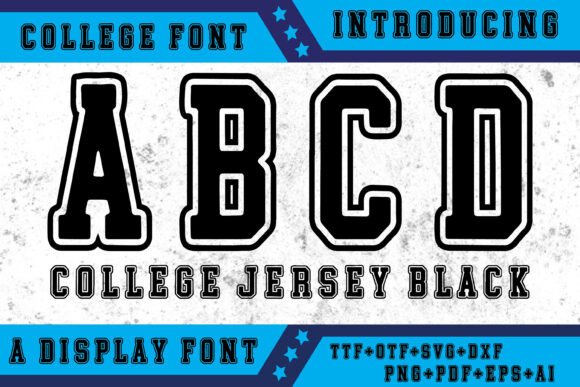
College Jersey Black
College Jersey Black – A Fonte que Transforma Seu Projeto em Vitória
Se você busca energia, tradição e personalidade vibrante para suas criações, a College Jersey Black é a escolha certeira. Essa tipografia, inspirada nos uniformes esportivos e nas artes gráficas de campus, combina contornos fortes e estrutura em bloco para entregar impacto visual imediato.
Ideal para branding, embalagens, logotipos e títulos chamativos, a fonte se destaca em projetos que precisam de voz autoritária sem perder a alegria contagiante. Veja a seguir os principais atributos que fazem da College Jersey Black um must‑have para designers:
- Design arrojado e block‑style: linhas grossas que garantem legibilidade mesmo em tamanhos reduzidos.
- Versatilidade esportiva: perfeita para uniformes, camisas de time, flyers de torneios e pôsteres de eventos atléticos.
- Aplicação em convites e papelaria: adiciona um toque de ousadia a convites de casamento, festões e materiais de marketing.
- Alto contraste e energia: os traços robustos criam presença marcante, ideal para cabeçalhos de sites, banners e anúncios.
- Compatibilidade multicanal: funciona perfeitamente em impressão, web, sinalização e produtos de merchandising.
Ao escolher a College Jersey Black, você garante:
- Um visual dinâmico que comunica competitividade e espírito de equipe.
- Facilidade de leitura em projetos de grande escala, como cartazes e outdoors.
- Um toque de alegria que revitaliza branding institucional e campanhas promocionais.
- Integração harmoniosa com cores vivas, realçando ainda mais a paleta de cores escolhida.
Em resumo, a College Jersey Black não é apenas mais uma fonte; é a alma do esporte e da celebração inserida no seu design. Experimente agora e sinta a diferença que um estilo tipográfico tão poderoso pode trazer ao seu próximo projeto!